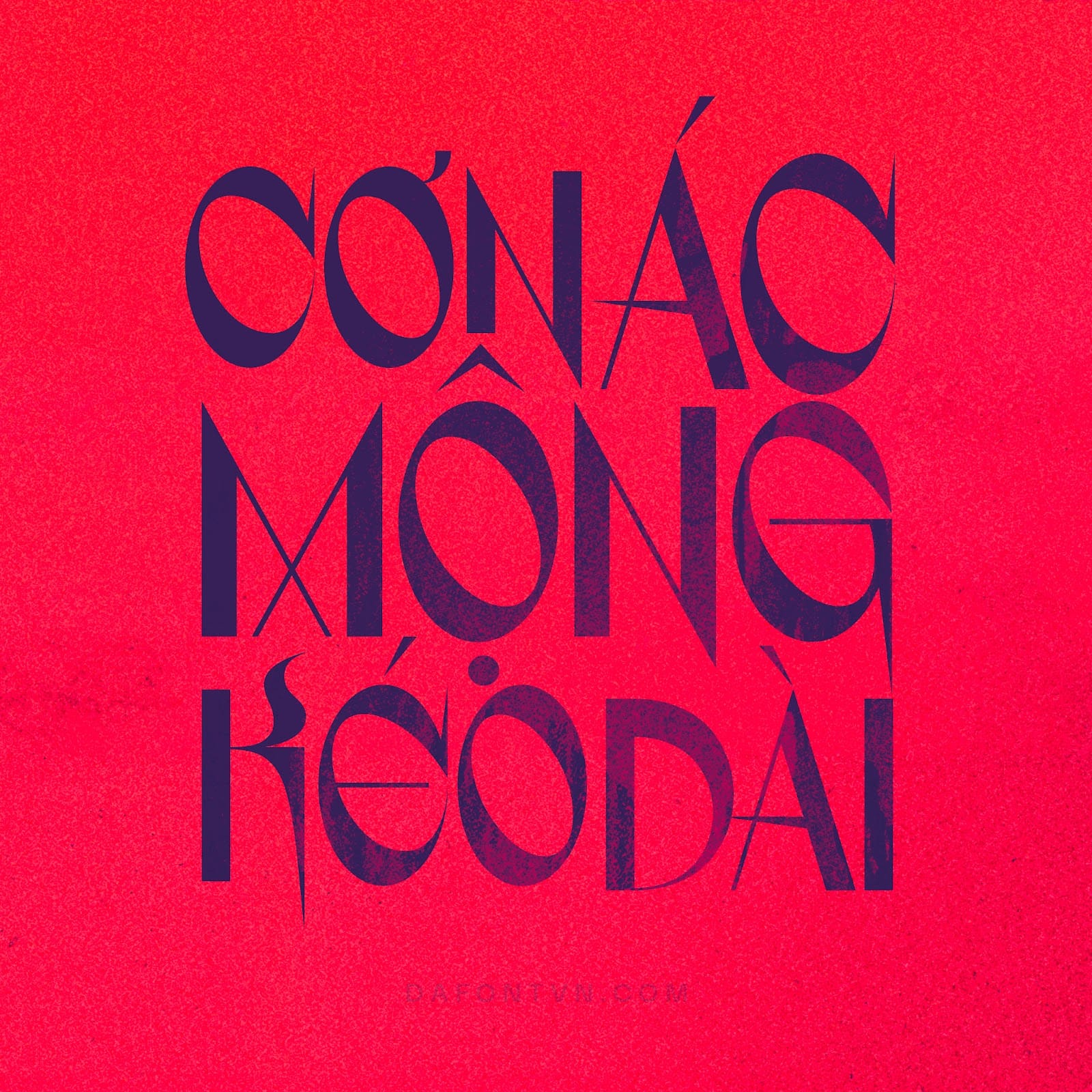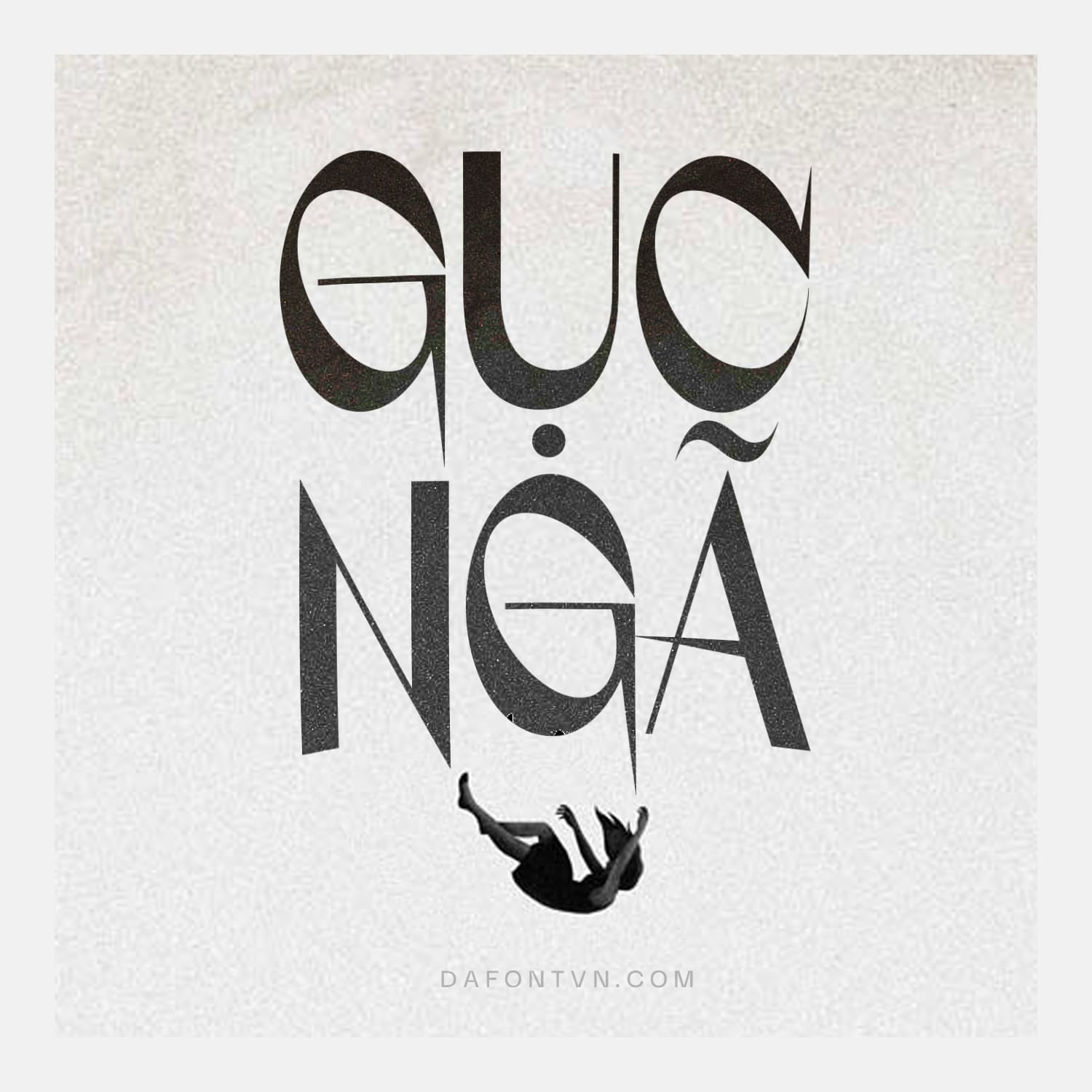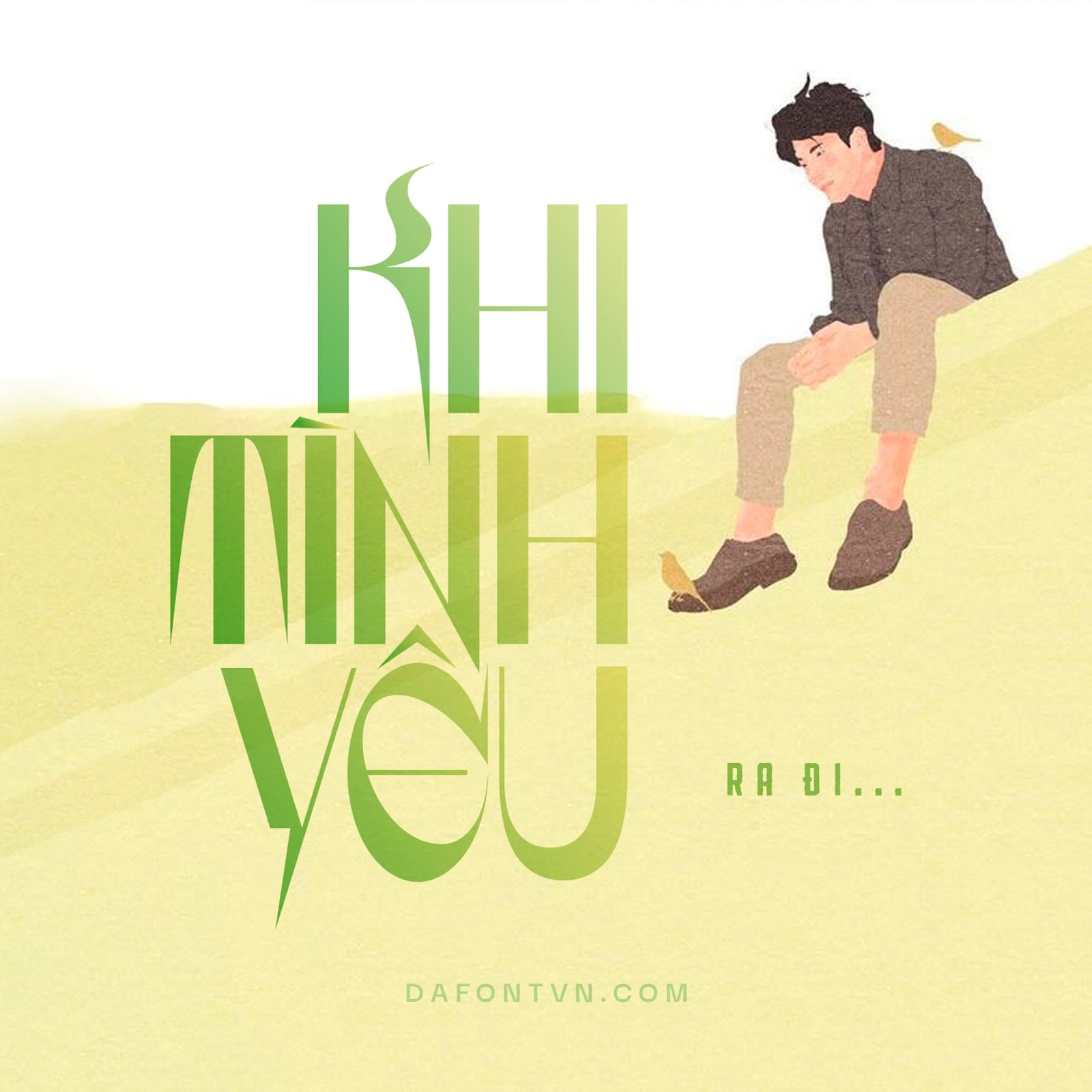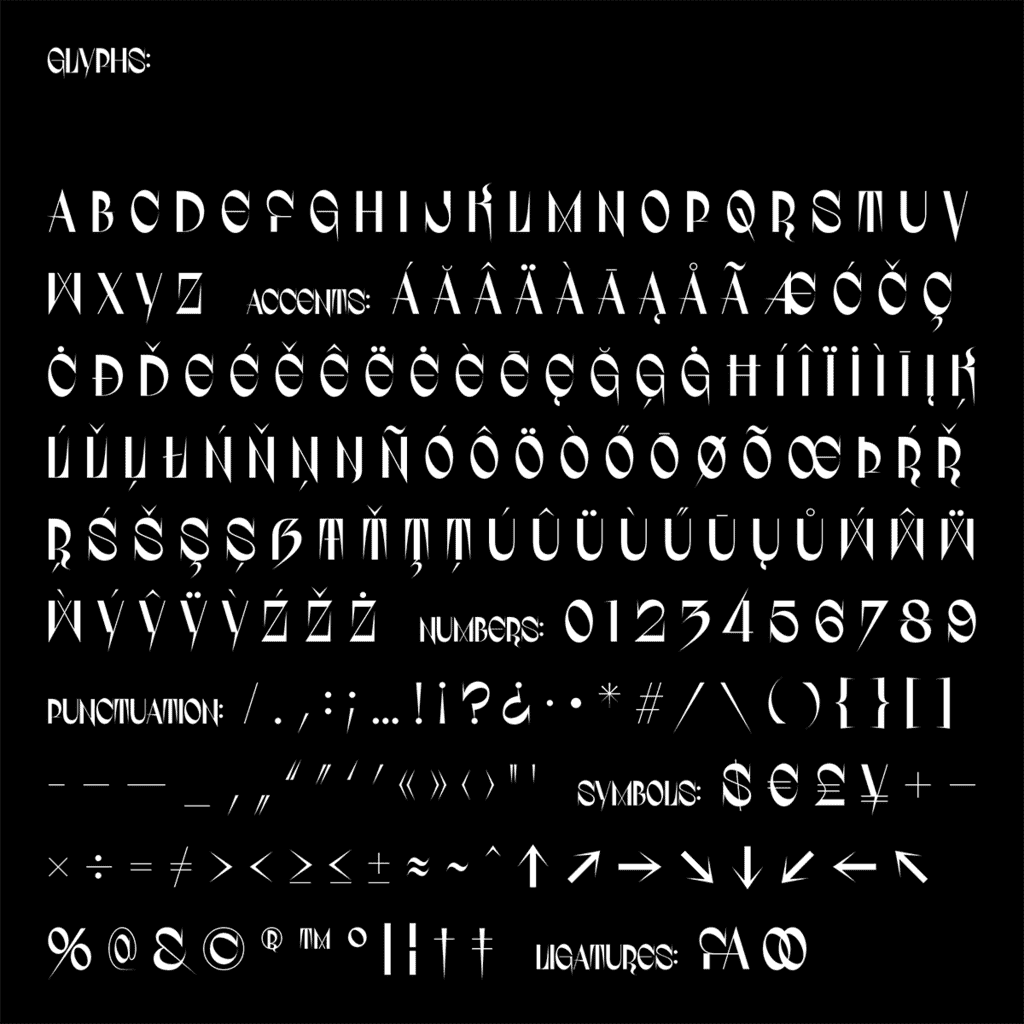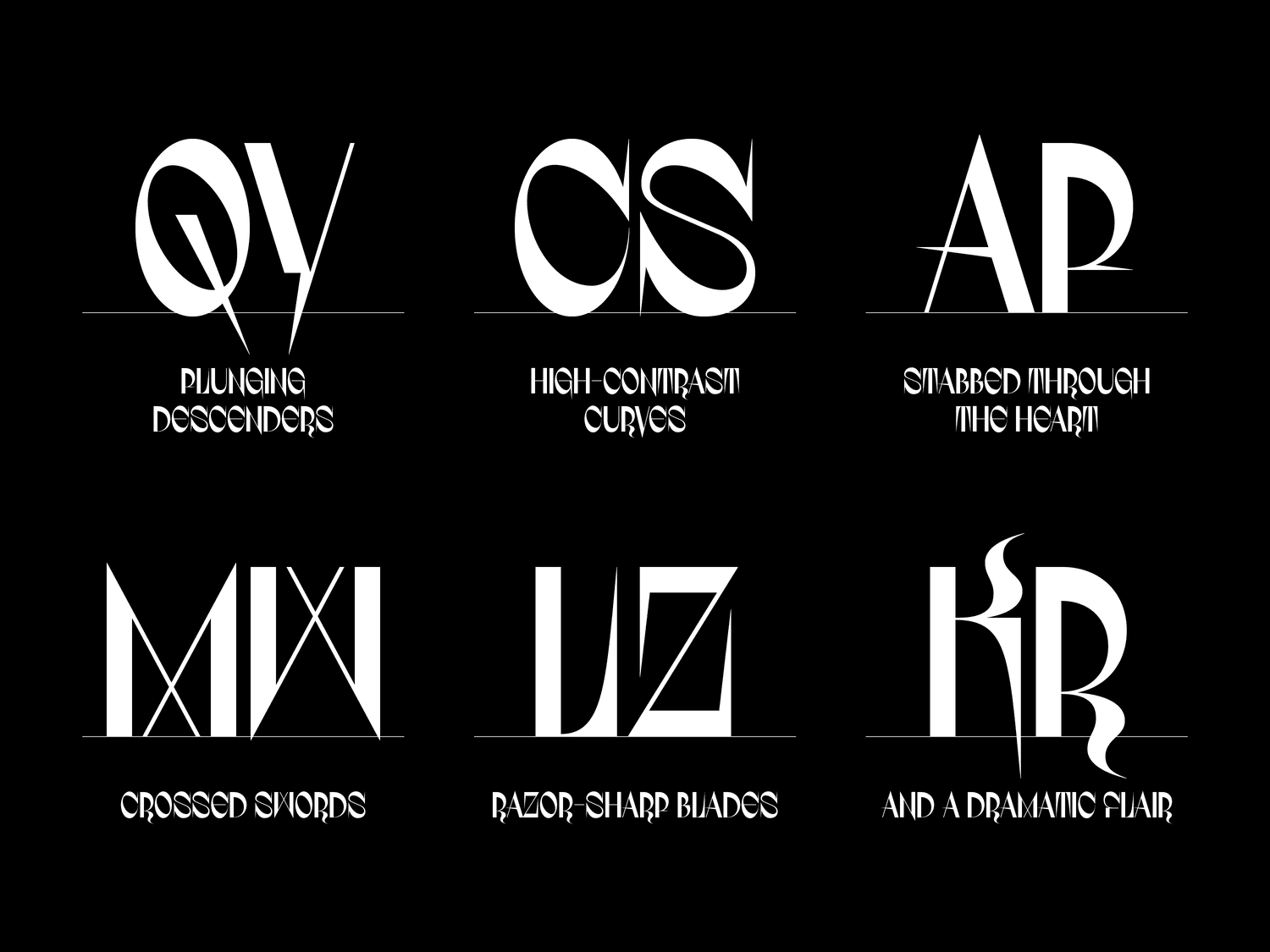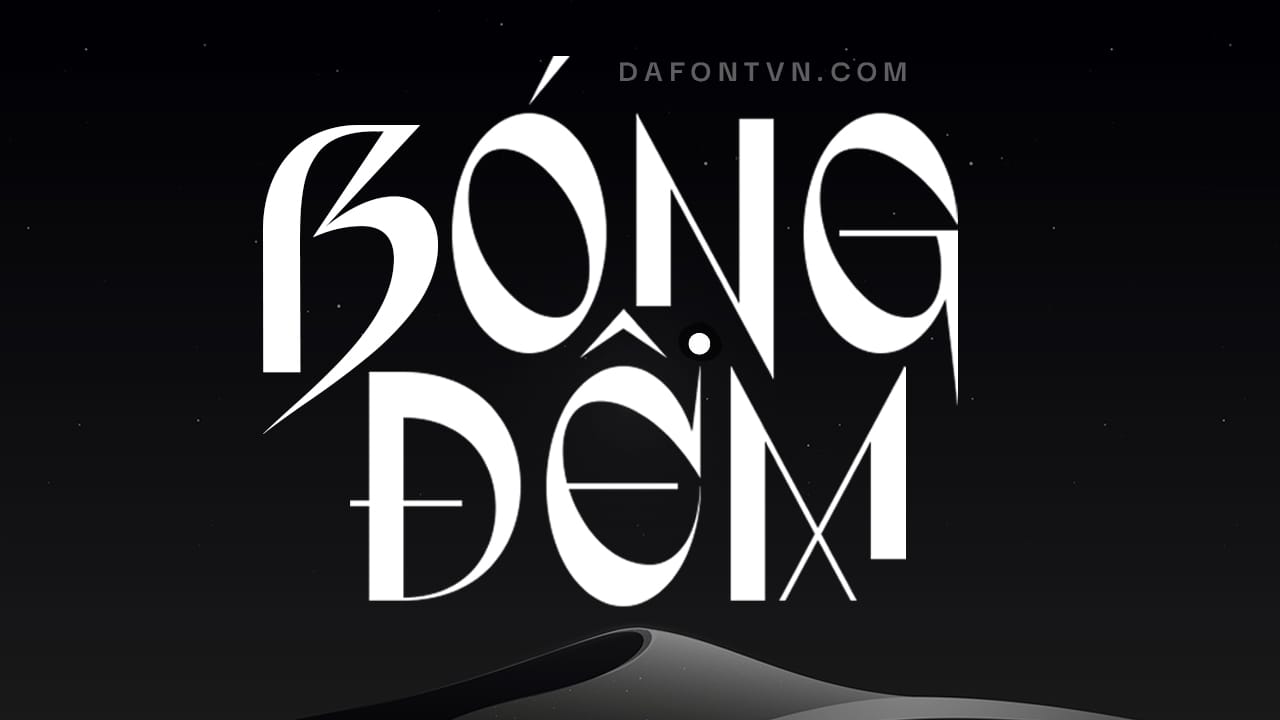
Villanelle Font – là một kiểu font chữ khá mới lạ và ấn tượng với các nét có độ tương phản cao và một sự tinh tế đặc biệt mang một phong cách mạnh mẽ, nếu bạn cần một kiểu font hiển thị độc đáo thì font Villanelle việt hóa rất phù hợp dành cho bạn.Font Villanelle với các chữ hoa cứng cáp vì vậy phù hợp cho nhiều các thiết kế khác nhau như poster, bìa sách, tạp chí hay những thiết kế đòi hỏi những điểm nhấn mạnh mẽ, ma mị hoặc những thiết kế cần một cái gì đó phá cách.Font được team DFVN việt hóa rất tỉ mỉ, chỉnh sửa và căn chỉnh lại dấu cũng như tối ưu hóa, ngoài ra được mã hóa PUA để bạn có thể dễ dàng sử dụng trên bất kỳ phần mềm nào.